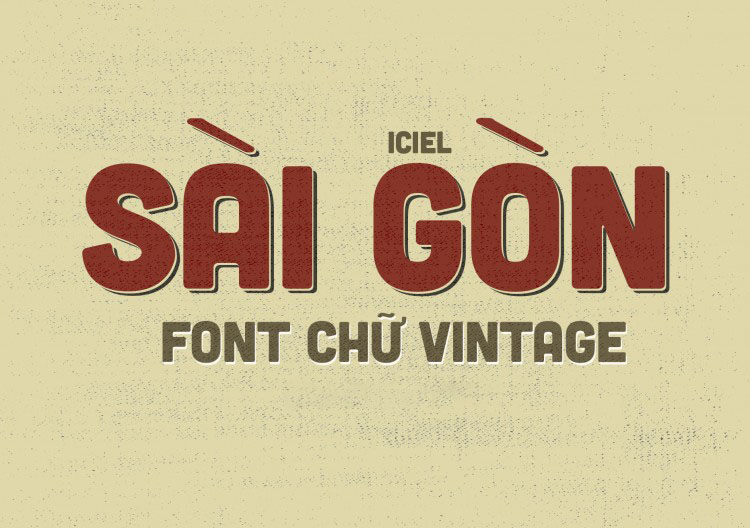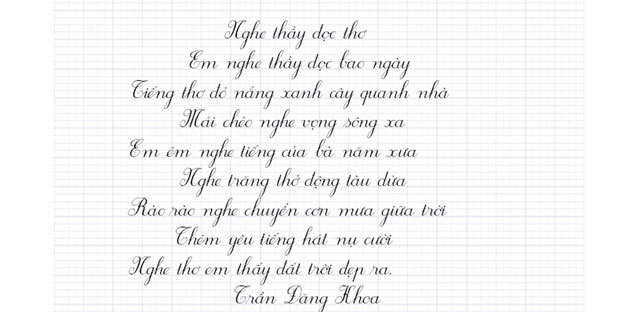
iCiel là một trong những hệ thống phông chữ Việt hóa chất lượng và đa dạng phong cách, từ hiện đại, tối giản đến nghệ thuật hoài cổ. Việc tải font iCiel cung cấp cho các kiến trúc sư và nhà thiết kế một kho tài liệu phong phú để hoàn thiện các hồ sơ dự án, bản vẽ phối cảnh và bộ nhận diện thương hiệu công trình.
Đặc điểm thẩm mỹ của hệ thống font iCiel Việt hóa trong thiết kế
Điểm lôi cuốn đặc trưng của dòng phông này chính là sự tỉ mỉ trong khâu xử lý dấu thanh tiếng Việt, giúp các ký tự đặc biệt luôn cân đối và hài hòa với cấu trúc chữ gốc. Khi thực hiện download font iCiel Việt hóa, người dùng sẽ nhận thấy sự ổn định về mặt thị giác trên mọi định dạng văn bản, hạn chế tình trạng lỗi font hay nhảy chữ thường gặp. Sự đa dạng của iCiel cho phép bạn linh hoạt thay đổi ngôn ngữ thiết kế tùy theo tính chất của từng hạng mục công trình cụ thể.
Hệ thống font iCiel còn được đánh giá cao nhờ khả năng truyền tải cảm xúc và định hình cá tính thương hiệu. Những bộ phông không chân mang lại cảm giác vững chãi cho văn phòng, nhà xưởng; trong khi các bộ phông Script uốn lượn lại tạo điểm nhấn lôi cuốn cho các khu homestay, nghỉ dưỡng. Đây là giải pháp phù hợp để thể hiện tư duy kiến trúc hiện đại, giúp thông điệp của chủ đầu tư được truyền đạt một cách mạch lạc và ấn tượng.
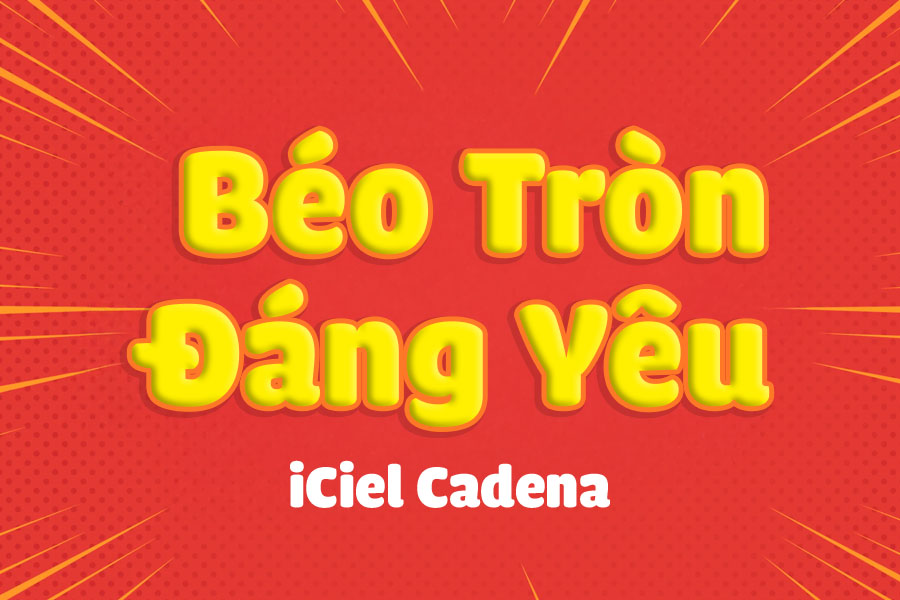
| Dòng Font tiêu biểu | Đặc tính thiết kế | Ứng dụng phù hợp |
|---|---|---|
| iCiel Cadena | Cấu trúc hình học, thanh thoát, hiện đại | Tải font iciel cadena cho logo, tiêu đề |
| iCiel BC Cubano | Nét dày, bo tròn, vững chãi | Download font icielbc cubano normal |
| iCiel Crocante | Vui nhộn, ngẫu hứng, thân thiện | Tải font iciel crocante cho decor |
| iCiel Lodestone | Phong cách retro, cá tính mạnh | Tải font icielbc lodestone cho bảng hiệu |
| iCiel Bambola | Mềm mại, uốn lượn, nghệ thuật | Download font iciel bambola cho thiệp |
Tư vấn trình bày: iCiel có rất nhiều biến thể độc đáo. Để bản thiết kế đạt hiệu quả thị giác ổn định, bạn nên sử dụng các bộ phông như iCielbc Cubano cho các đề mục lớn và phối hợp cùng một font không chân tối giản cho phần nội dung thuyết minh chi tiết, giúp tổng thể bố cục trông chuyên nghiệp hơn.
03 Ứng dụng phông chữ iCiel vào dự án kiến trúc thực tế
Nhờ diện mạo đa dạng và khả năng thích ứng linh hoạt, việc sử dụng các mẫu từ bộ tải font iCiel Việt hóa mang lại giá trị thực tế cao trong quá trình triển khai dự án:
- Hệ thống nhận diện cho Homestay & Resort: Sử dụng các dòng phông nghệ thuật như iCiel Bambola hoặc iCiel Crocante cho biển hiệu giúp không gian nghỉ dưỡng toát lên vẻ thư thái và có gu thẩm mỹ riêng, thu hút khách khách hàng ngay từ cái nhìn đầu tiên.
- Trình bày hồ sơ năng lực dự án: Việc sử dụng iCiel Cadena cho các tiêu đề chương giúp hồ sơ trông hiện đại, sạch sẽ, thể hiện tư duy tổ chức thông tin khoa học của đơn vị thiết kế và thi công.
- Hệ thống biển chỉ dẫn văn phòng: Nét chữ dày và rõ ràng của tải font icielbc cubano rất ăn ý khi gia công chữ nổi laser trên mica hoặc inox cho các khu văn phòng container, giúp việc nhận diện khu vực công năng trở nên dễ dàng.
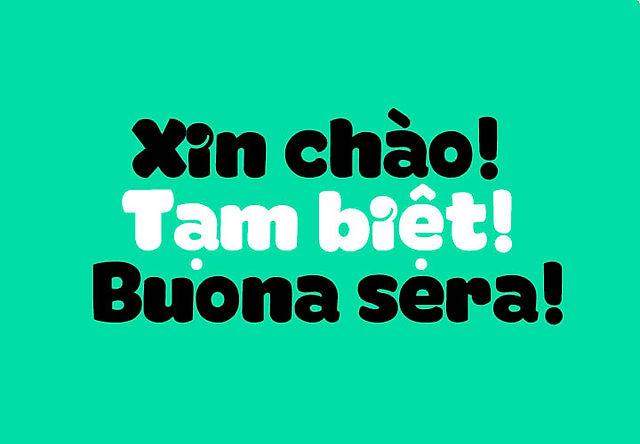
03 Lưu ý kỹ thuật để khai thác tối đa bộ phông iCiel chuyên nghiệp
Để khai thác hiệu quả vẻ đẹp của dòng phông đa năng này mà không làm rối mắt người xem, người thiết kế nên lưu tâm một số kinh nghiệm kỹ thuật sau:
- Lựa chọn phong cách phù hợp với vật liệu: Khi thiết kế cắt chữ nổi cho nhà lắp ghép, bạn nên ưu tiên các phông có cấu trúc chắc chắn như iCielbc Lodestone để đảm bảo độ bền cơ học và tính sắc sảo sau khi thi công thực tế tại công trường.
- Kiểm soát khoảng cách dòng và chữ: Đối với các phông đậm như Cubano, bạn nên nới rộng khoảng cách giữa các chữ cái một chút khi trình bày ở kích thước nhỏ để tránh hiện tượng bết dính nét, giúp văn bản thông thoáng hơn.
- Tính đồng bộ trong hệ thống tài liệu: Hãy duy trì một phong cách iCiel xuyên suốt từ bản vẽ AutoCAD đến slide Powerpoint thuyết trình dự án để tạo nên sự nhất quán trong hình ảnh thương hiệu chuyên nghiệp của đơn vị.